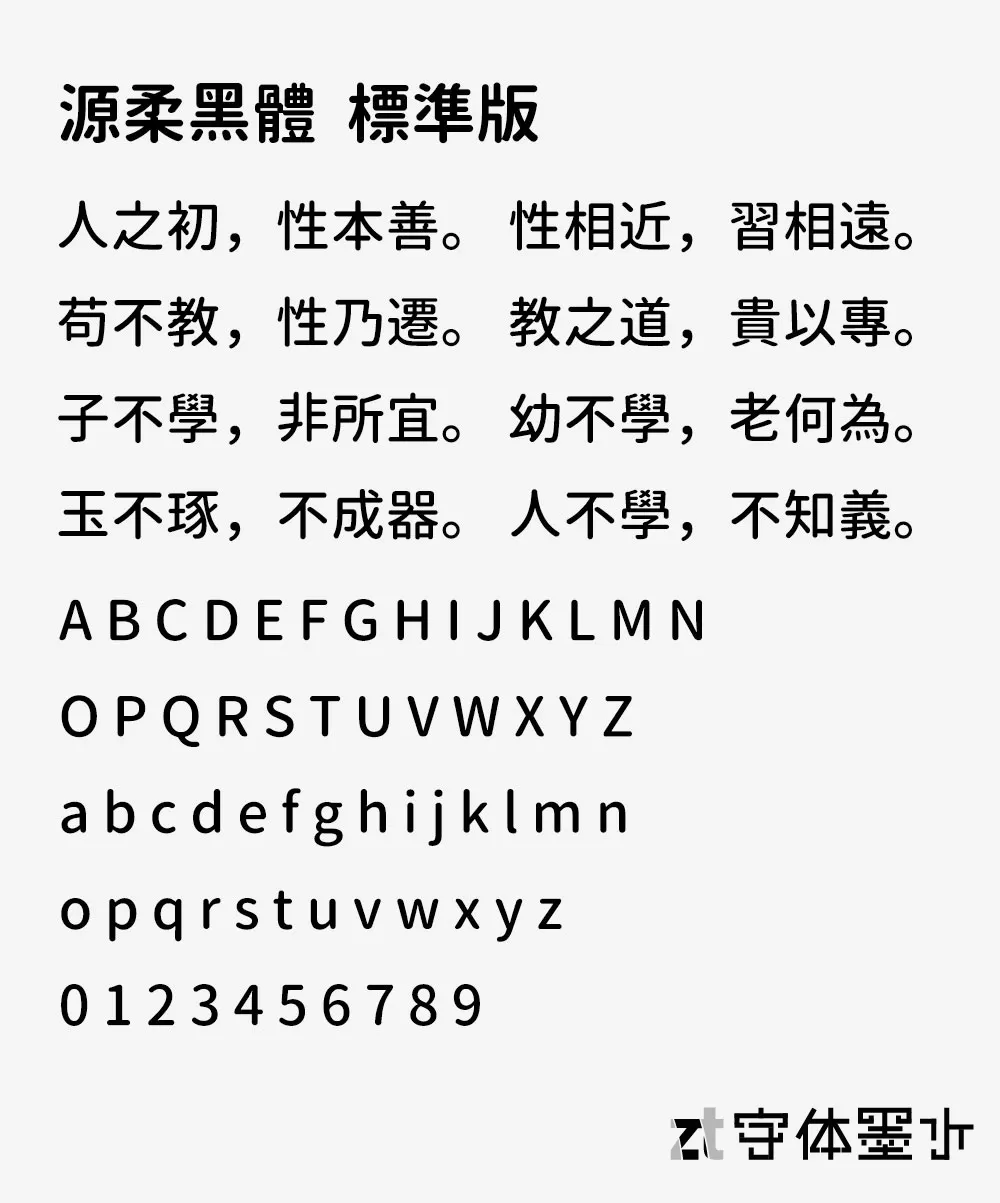
首页 / 黑体 / 【源柔黑体 源柔ゴシック】应用场景非常广泛的免费字体 【源柔黑体 源柔ゴシック】应用场景非常广泛的免费字体 zitiink · 黑体 · 2026年1月9日 4 0 字体预览 源柔黑体 已使用字体 输入预览文字 重置 常规 400 源柔黑体 ABC abc 123 · 这是一段字体预览文字。 粗体 700 源柔黑体 ABC abc 123 · 这是一段字体预览文字。 斜体 400 源柔黑体 ABC abc 123 · 这是一段字体预览文字。 源柔黑体(源柔ゴシック)和源真黑体(源真ゴシック)是日本 自家製フォント工房基于开源字体“思源黑体”修改制作衍生而来,支持繁体中文以及日文。两款字体都是开源免费的,应用场景非常广泛。 源柔黑体一共发布了 3 个版本,分辨是标准版、L、X。它们的区别在于圆角的圆润程度不同,L 圆角最小 (最尖),X 圆角最大 (最圆),而标准版则是介于两者之间。每个版本都有 7 种字重,3种字形样式 (包括等宽字体)。 下载资源 免费 字体全名:: 源柔黑体 授权类型:: 免费商用 版权声明 本文标题:【源柔黑体 源柔ゴシック】应用场景非常广泛的免费字体 本文链接:https://ziti.ink/67.html 版权声明:本站文章除特别声明外,均采用 CC BY-NC-SA 4.0 许可协议,转载请注明出处! 上一篇 演示魁本楷书 2026-01-08 下一篇 暂无更多文章 暂无评论 取消回复 评论内容 * 发表评论